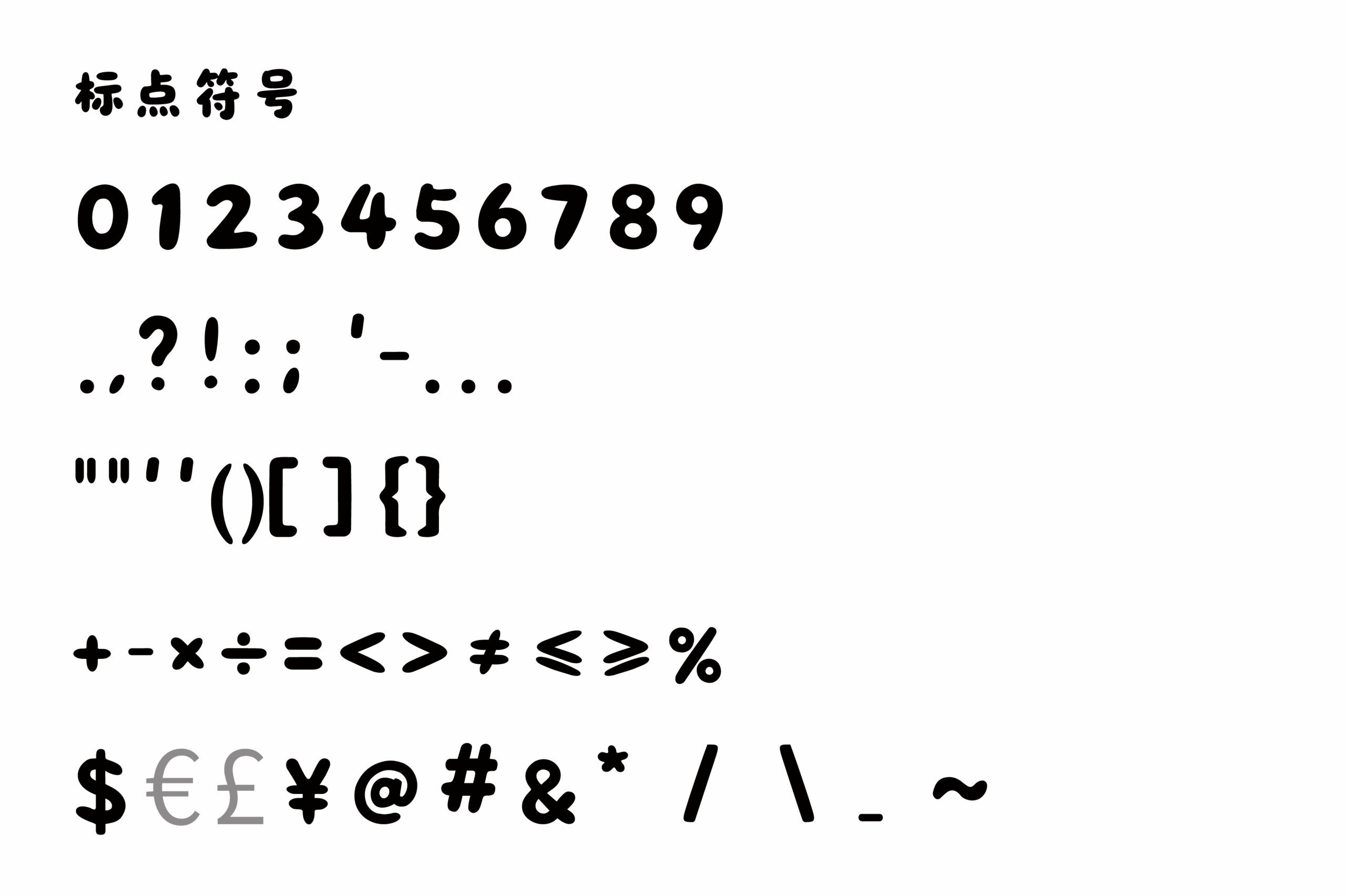
乐米元气团团体
乐米元气团团体是杭州乐米网络科技有限公司设计的一款免费商用字体。设计以卡通萌趣为核心,笔画圆润饱满、字形活泼,呈现出“圆滚滚”的视觉风格,整体充满元气与活力,如同自带“快乐buff”,适合应用于健身、美食、生活方式等需要传递轻松愉快氛围的内容设计。
如第1张图所示,上下“乐米元气团团体”字样在黑白正反色的对比中,字体呈现出鲜明的圆润风格,笔画无尖锐转折,整体造型饱满、活泼。在白色背景上,黑色字形清晰、醒目,充满动感;在黑色背景上,白色轮廓同样稳定、可爱。“圆润、活泼、萌趣”的特质在不同背景下均得到良好呈现,验证了作为一款卡通字体的基本可识别性。
第2张图的字母表,大写字母(A-Z)与小写字母(a-z)均遵循圆润、饱满的设计原则,笔画粗细均匀,转折处均为圆弧处理。所有字母在视觉重量、圆润曲线与整体节奏上保持了内在的统一,形成了一套风格协调、视觉友好的完整字符系统,为“适合儿童与年轻群体”的定位提供了坚实基础。
第3张图所展示的符号集,数字、标点、括号、运算符号、货币符号等,所有符号都延续了字母部分的圆润、萌趣风格。这意味着在进行涉及丰富符号的儿童产品、食品包装、社交媒体、文创周边等设计时,能确保视觉语言从核心到细节的绝对统一、亲和力与趣味性。
第4张图的段落排版,在这段关于积极生活态度的文本中,字体形成了均匀、活泼、富有亲和力的文本块。圆润的字形、宽松舒适的字间距、合理的行宽共同构成了轻松、愉快、富有引导性的阅读节奏。卡通萌趣风格特有的快乐感与元气感,为这段鼓励性文字注入了强烈的积极情绪与感染力,阅读体验轻松而愉悦。这完美印证了其“适配不同尺寸创作”、“保持清晰视觉效果与可爱质感”的设计目标,尤其适合需要快速传递快乐、活力与亲近感的场景。
总的来说,乐米元气团团体是一款在“卡通萌趣美学”、“高易读性”与“多场景适应性”方面表现突出的免费商用字体。它通过极致的圆润笔画处理、宽松舒适的字间距、完备的字符符号支持,为用户在需要营造活泼、可爱、富有元气与亲和力视觉氛围的设计场景中,提供了一个可靠、实用且情绪价值鲜明的解决方案。